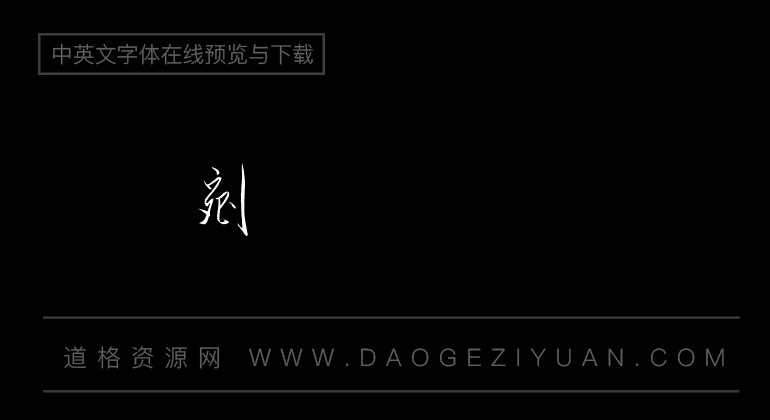
金梅新毛笔草楷字体是一款经典的毛笔草书字体,它具有优美的笔画和流畅的曲线,极具古典气质。它的字体宽度比较宽,笔画粗细比较均衡,比较适合写毛笔草书,也可以用于书法、绘画等。它有着精致的笔画结构,结构清晰,曲线流畅,富有古典气质,极具艺术感。文件名:JinMeiXinMaoBiCaoKai-1.ttf
金梅新毛笔草楷是一款非常不错的手写艺术字体,具有很好的视觉感,适合于文化类的宣传设计、商业类品牌的广告和产品包装设计以及个性化文字排版等较多场景。